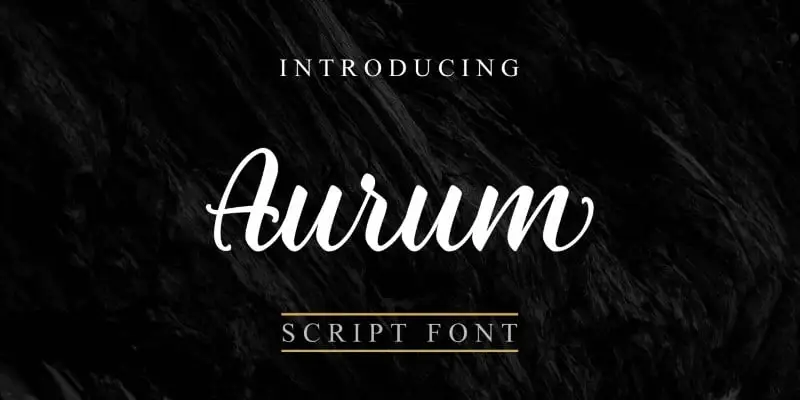
Aurum Script Font é uma elegante fonte de script que carrega consigo a beleza do estilo manuscrito. Desenvolvida pela Stasy Font, essa tipografia simples e luxuosa é perfeita para projetos profissionais que buscam dar um toque único e sofisticado à sua marca. Quando combinada com estilos de escrita manuscritos artesanal, ela transforma qualquer projeto em algo ainda mais poderoso e impressionante. Estamos certos de que essa fonte se destacará como uma escolha ótima para qualquer iniciativa branding ou design gráfico que deseje exalar elegância e sofisticação através do uso da tipografia.